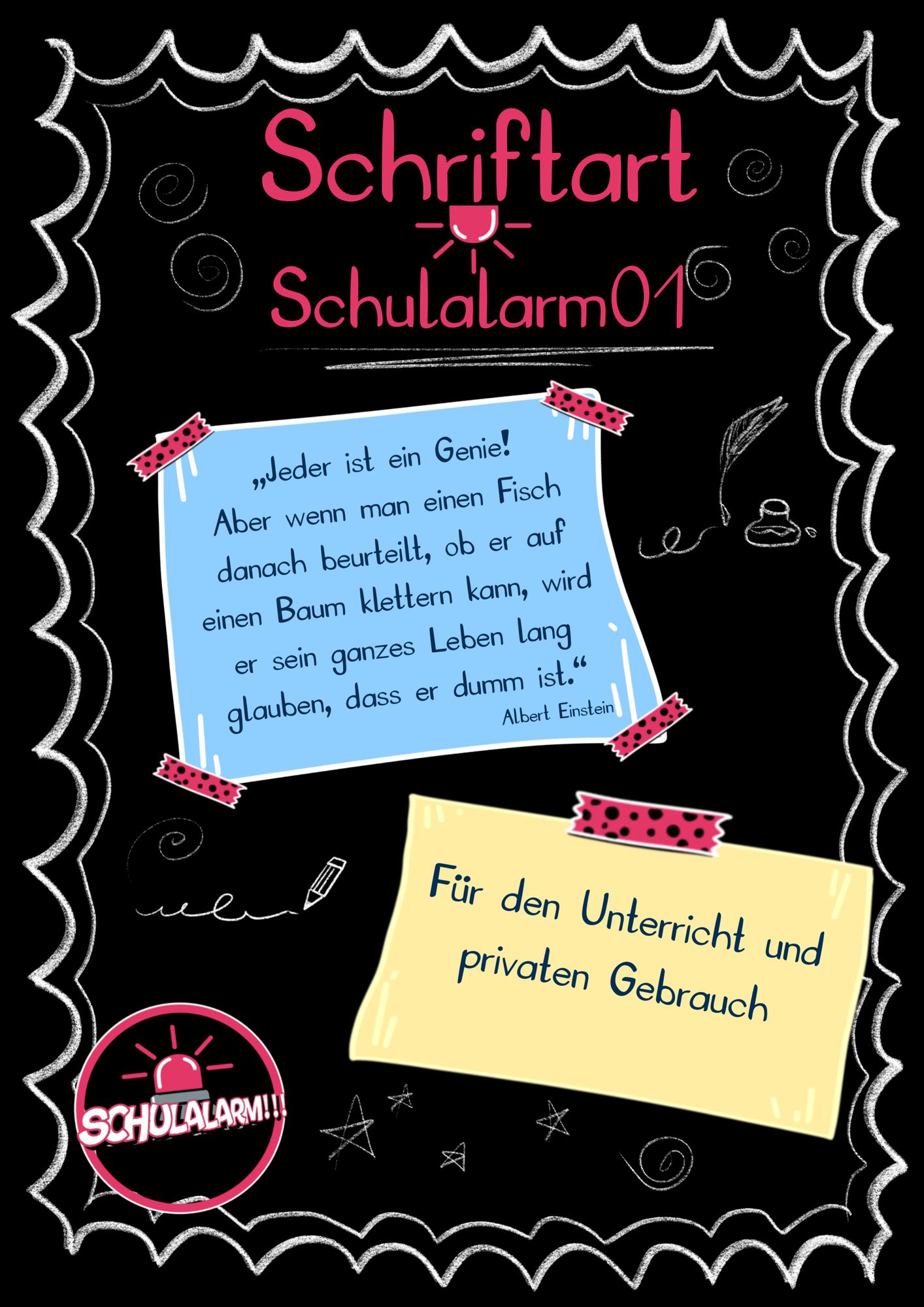
selbst erstellte Schriftarten - Schriftart: Schulalarm01 - Schulalarm!!! - Deckblatt
Eine gut lesbare Schrift, die von den Proportionen her gut im Zusammenhang mit der Grundschullineatur verwendet werden kann.
Schriftart: Schulalarm01